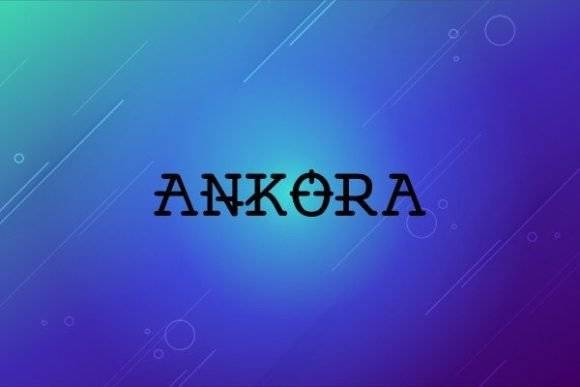
Este download inclui a fonte Ankora, uma tipografia estilizada criada para fluxos de trabalho de artesanato, incluindo corte digital e designs prontos para impressão. Como uma fonte completa, ela oferece contornos nítidos e formas artísticas para integração perfeita com softwares e máquinas de artesanato.
Sua estrutura fluida e espaçamento bem pensado a tornam ideal para uso em recorte de vinil, sinalização impressa e modelos digitais. Seja para criar citações, estampas para roupas ou decoração para casa, a Ankora oferece charme escalável e precisão criativa.